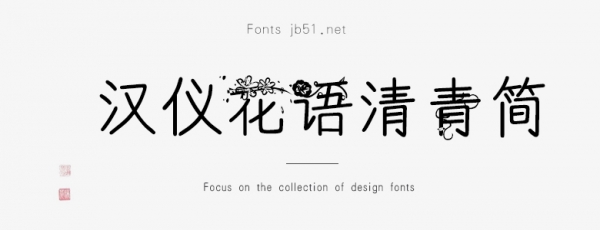
漢儀花語(yǔ)清青簡(jiǎn)是由漢儀字庫(kù)出品,字體筆觸適中,字形端正,以花朵作為點(diǎn)綴,具有很好的視覺感,適合應(yīng)用于藝術(shù)設(shè)計(jì)、平面宣傳設(shè)計(jì)、網(wǎng)頁(yè)設(shè)計(jì),書法字帖等領(lǐng)域,需要的朋友可以前來(lái)本站下載。